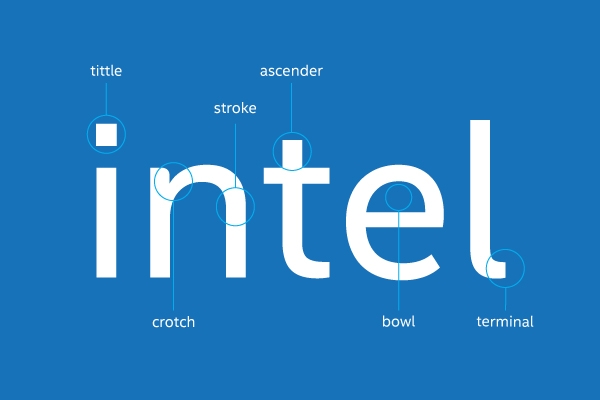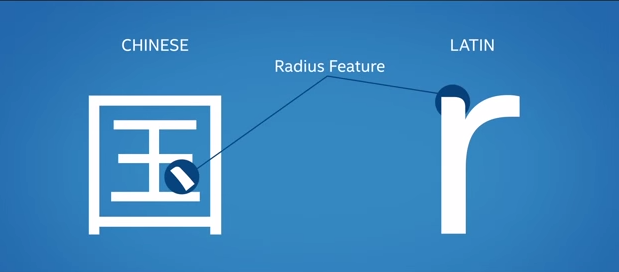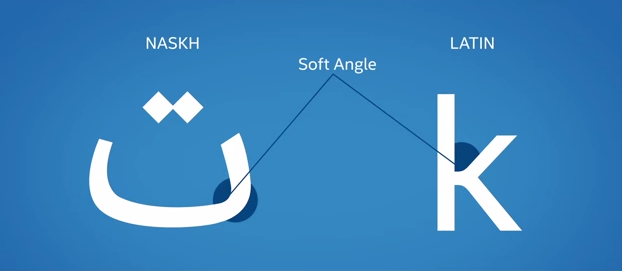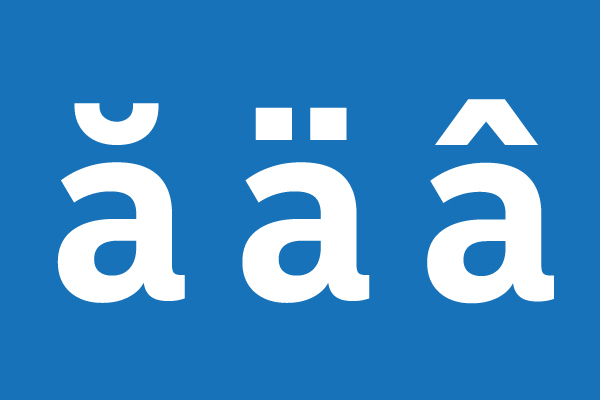
Intel thay đổi font chữ logo thương hiệu
Intel thay đổi font chữ logo thương hiệu, dễ đọc hơn và phù hợp với nhiều loại ngôn ngữ
Gã khổng lồ Intel vừa mới tạo ra font chữ mới cho logo của hãng, tên là Intel Clear, được thiết kế để dễ đọc hơn trên màn hình và có thể được sử dụng trong nhiều bảng chữ cái khác nhau. Và font mới này thuộc quyền sở hữu của chính Intel vì thế họ không phải trả tiền phí khi sử dụng.
Font chữ cũ của Intel chỉ có sẵn cho các bảng chữ cái Latinh 26 ký tự - ví dụ như tiếng Anh và tiếng Pháp - với những ngôn ngữ như tiếng Hoa, Ả rập và Nga thì Intel phải dùng đến font chữ khác. Font cũ cũng khó đọc hơn khi ở kích thước nhỏ.
Font chữ mới được phát triển bởi Red Peak và Dalton Maag. Những thay đổi chỉ nhằm giúp cho nó dễ đọc hơn. Ví dụ, font Intel Clear cân xứng hơn, tròn trịa hơn và dấu chấm trên chữ i là hình vuông.
Như vậy là bộ font chữ mới của intel sẽ có cho hầu hết các ngôn ngữ trên thế giới, từ tiếng Hindi hay Ả Rập, từ ngôn ngữ tượng hình như Trung Quốc hay tiếng dựa vào Latin như Việt Nam đều dùng một bộ font có cùng đặc điểm thiết kế, là đặc điểm "Intel Clear"
Font chữ mới cho logo của Intel sẽ được sử dụng trong tất cả các hoạt động truyền thông của hãng.